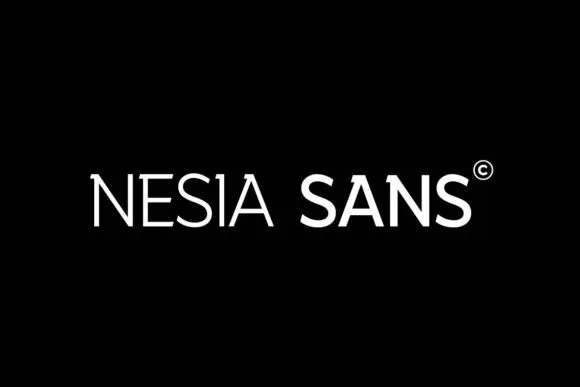
Nesia Sans Font – Fonte Grátis
Nesia Sans Font
Nas páginas do nosso site de fontes, você encontrará uma vasta seleção de tipos de letras para tornar ainda mais atraente sua próxima criação visual. Hoje, apresentamos a ‘Nesia Sans Font’, um design sofisticado criado pelo incrível artista Ryan Vierra através da plataforma 99designs. Esta fonte sans serif é uma verdadeira joy de criar com ela, seus traços elegantes e linhas leves trazem uma sensação suave e moderna que pode transformar o seu trabalho em algo realmente especial. Ela oferece um toque discreto de contraste sem tirar nem pôr nada da sua simplicidade e aguçada aparência, tornando-a perfeitamente projetada para inspirar a criação de designs imprevisíveis e impactantes. Com certeza, esta font é uma escolha inteligente para quem busca um toque moderno e sofisticado em seus trabalhos. Adquira sua ‘Nesia Sans Font’ agora e dê vida ainda mais ao seu projeto!